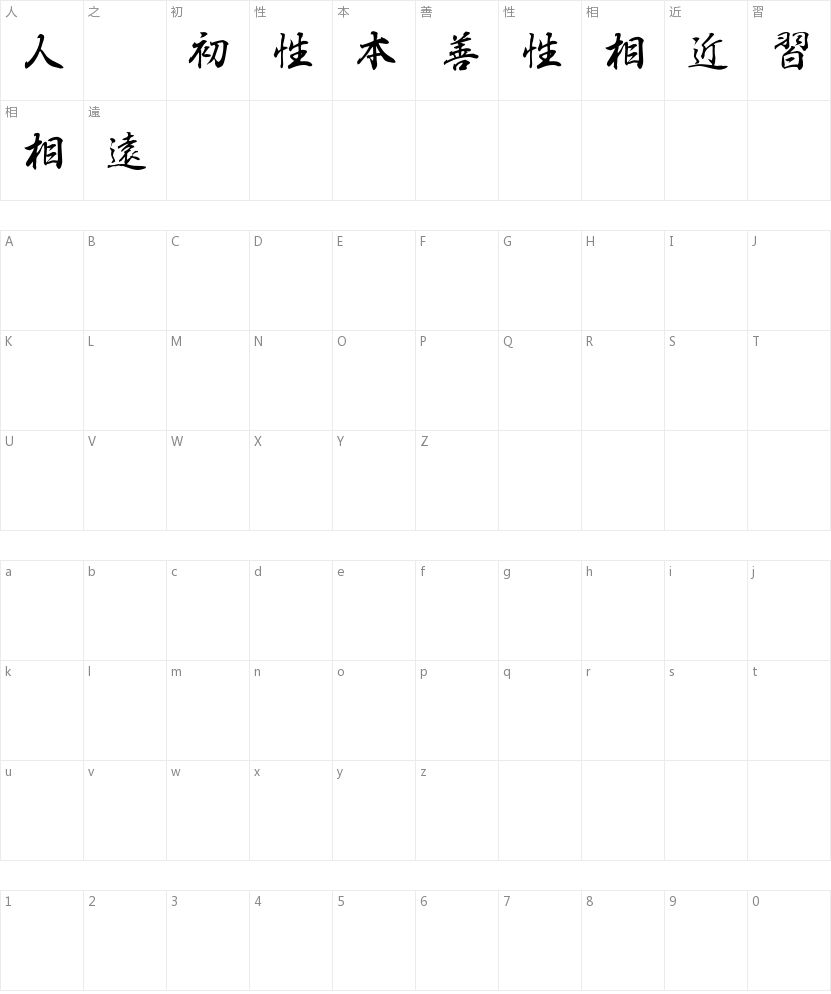
白舟行书教汉
白舟行书教汉字体是一种经典的汉字字体,由晚清时期书法家白舟先生发明,他在书法上追求清新、精致、细腻的风格,以及笔画的精准与细腻。白舟行书教汉字体的字体特点是比较规整,笔画比较精细,比较细腻,比较清新,比较精致。白舟行书教汉字体的字体特点是比较规整,笔画比较精细,比较细腻,比较清新,比较精致,同时也比较轻巧,比较易读,比较易记,比较易学习。
白舟行书教汉是一款非常不错的手写艺术字体,具有很好的视觉感,适合于文化类的宣传设计、商业类品牌的广告和产品包装设计以及个性化文字排版等较多场景。